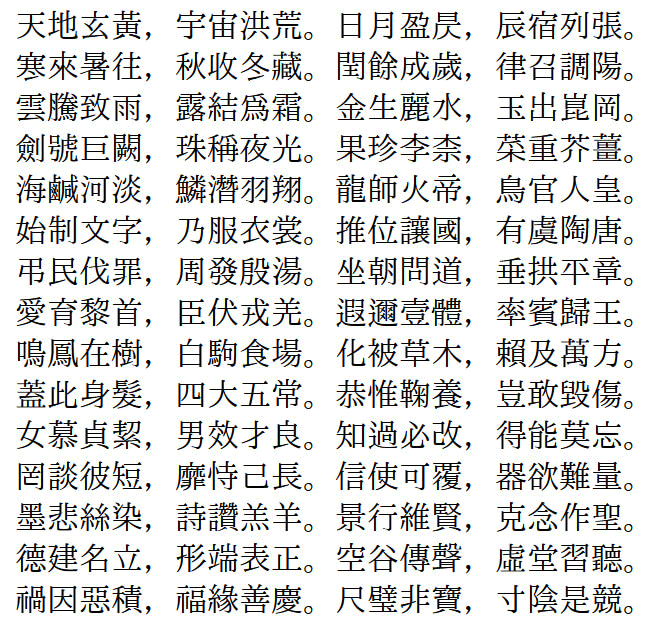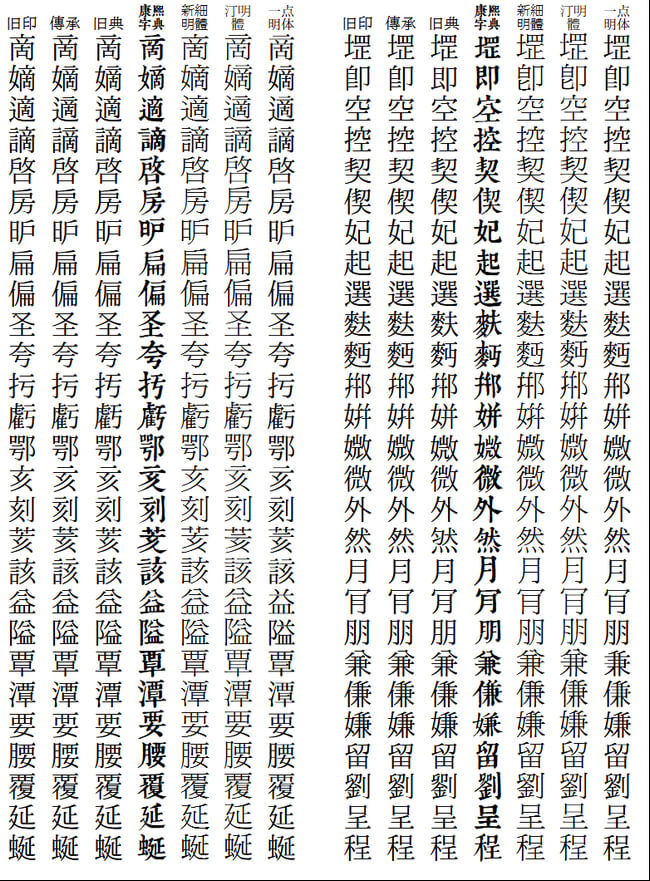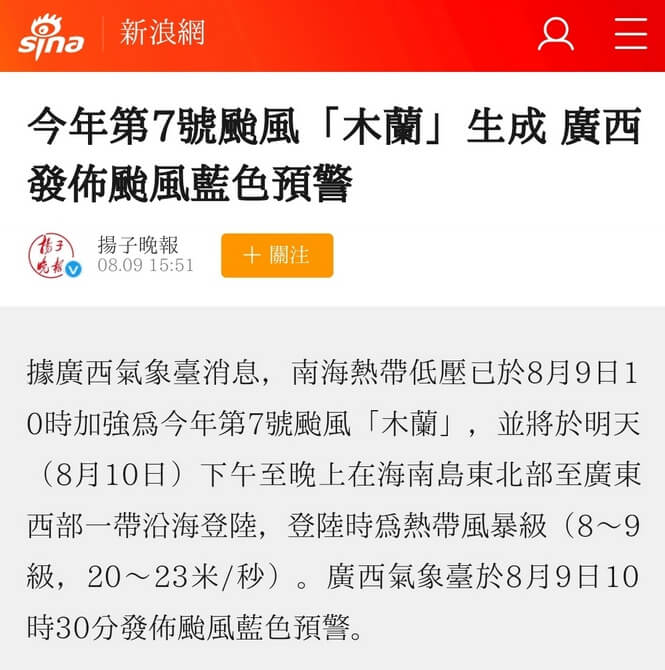
华英明朝(Huaying Mincho)是一套拥有传承字形、旧字形风格的中文字体。华英明朝共提供 3 种字形风格,并带有符合 IVD_Charts_Moji_Joho 标准的异体选择器。
1.华英明朝旧印体
旧印刷体,字形接近旧版Windows新细明体。
2.华英明朝传承体
传承字形,字形部件较为统一。
3.华英明朝旧典体
接近《康熙字典》中的字形,字形部件不统一。
4.华英明朝繁体
由传承体修改,简入繁出的字体,可根据文字内容动态匹配一简多繁的情况。
传承体预览
版本对比
繁体版预览(文字为简体)